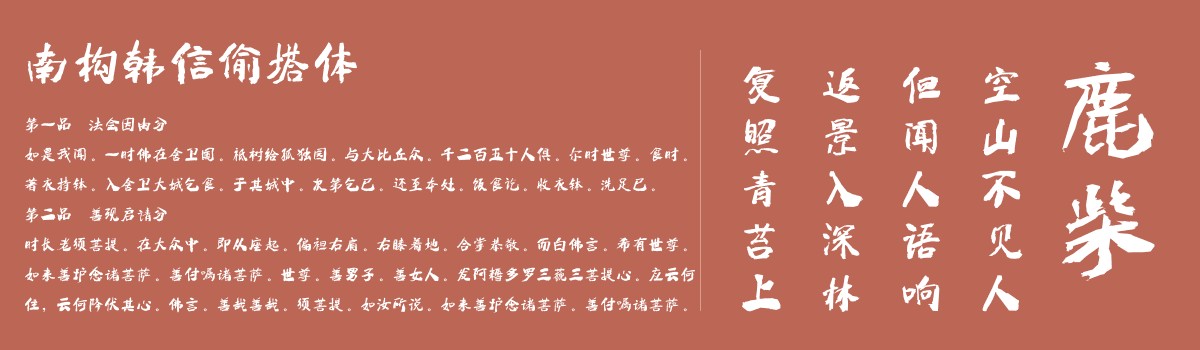
南构韩信偷塔体
这是一款个性锋芒,粗狂有力的行书手写体字体,命名为韩信偷塔体,是结合当时韩信的性格以及历史故事背景而体现。
关于韩信
韩信,淮阴人,秦末最著名的战将,谋略家。微时,曾受过胯下之辱,还受漂母一饭之恩。秦末大乱,他先投项羽,不得重用,转投刘邦,开始,也没有被重视。只有萧何、夏侯婴等人赏识他,极力推举他为将。《史记·淮阴侯列传》中萧何称韩信“国士无双”。
登坛拜将后,果然在韩信的谋划和亲自领兵打击下,项羽一步步被削弱,最终十面埋伏,在垓下击败项羽。
楚汉相争结束,韩信被封为楚王,刘邦评价曰:“战必胜,攻必取,吾不如韩信。”韩信是中国军事思想“谋战”派代表人物,被后人奉为“兵仙”、“战神”。“王侯将相”韩信一人全任。但因其功高盖主,又不知收敛,使刘邦渐渐失去了对他的信任。汉朝建立后解除兵权,徙为楚王,被人告发谋反,降为淮阴侯,最后,在吕后和萧何的合谋下,斩于钟室。